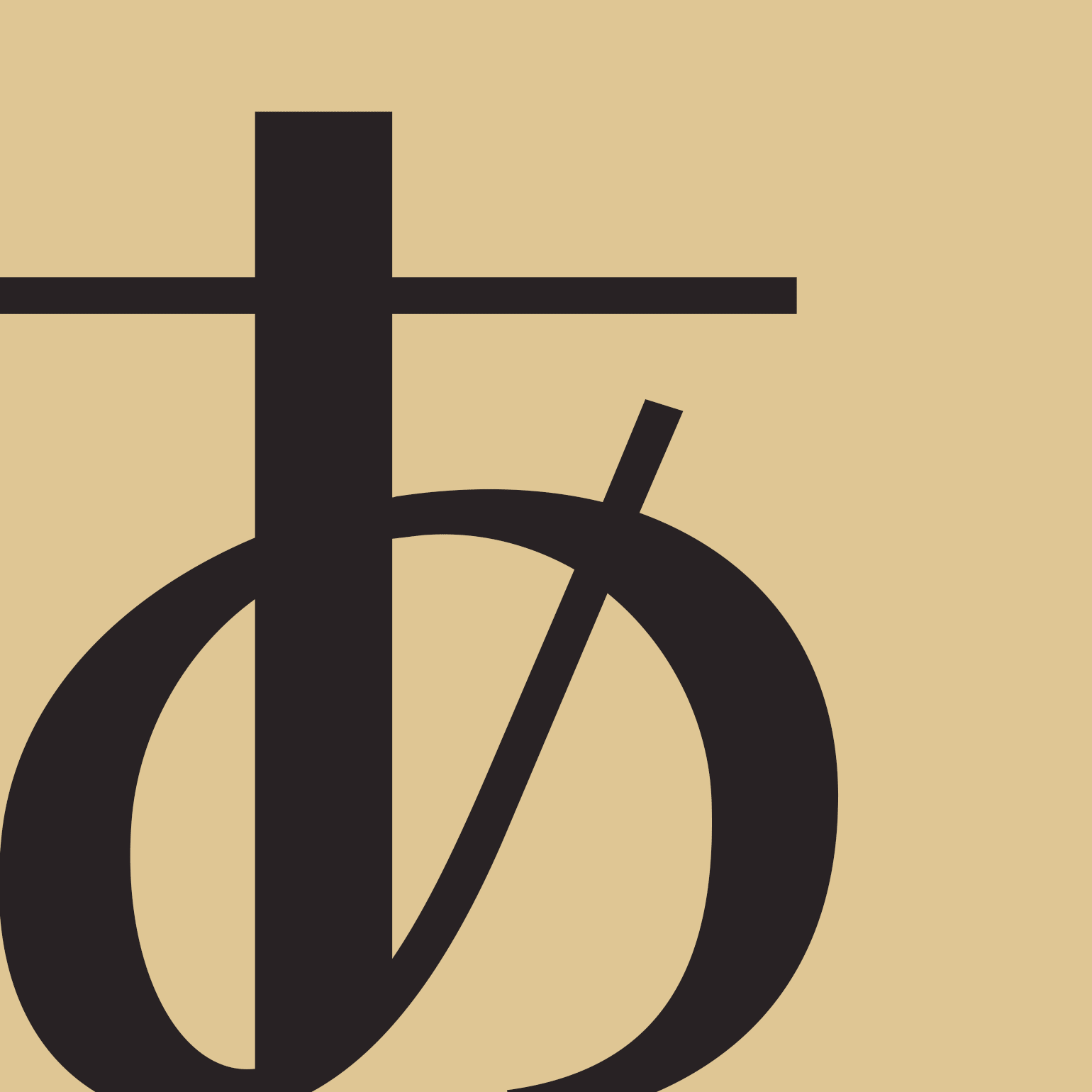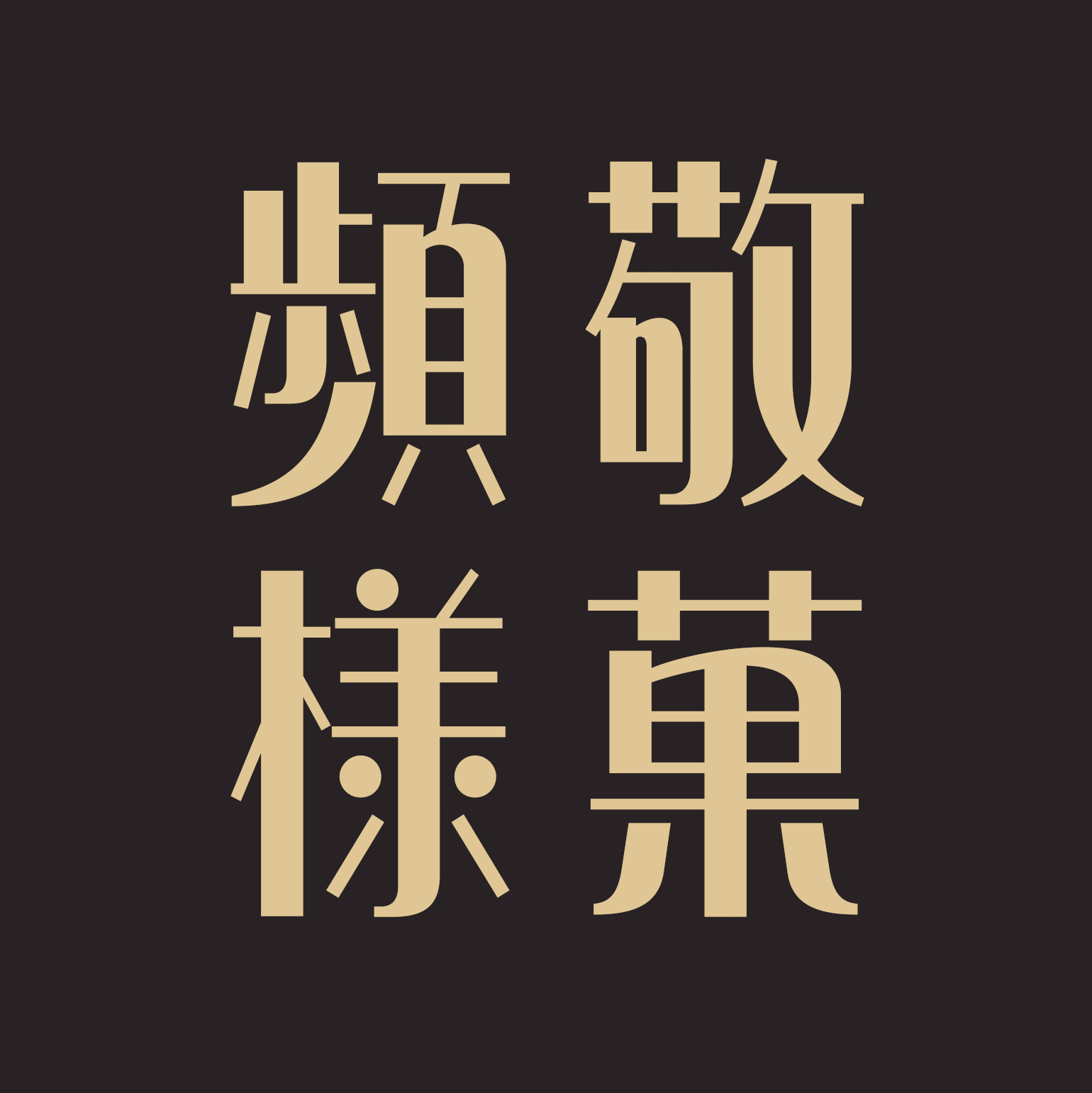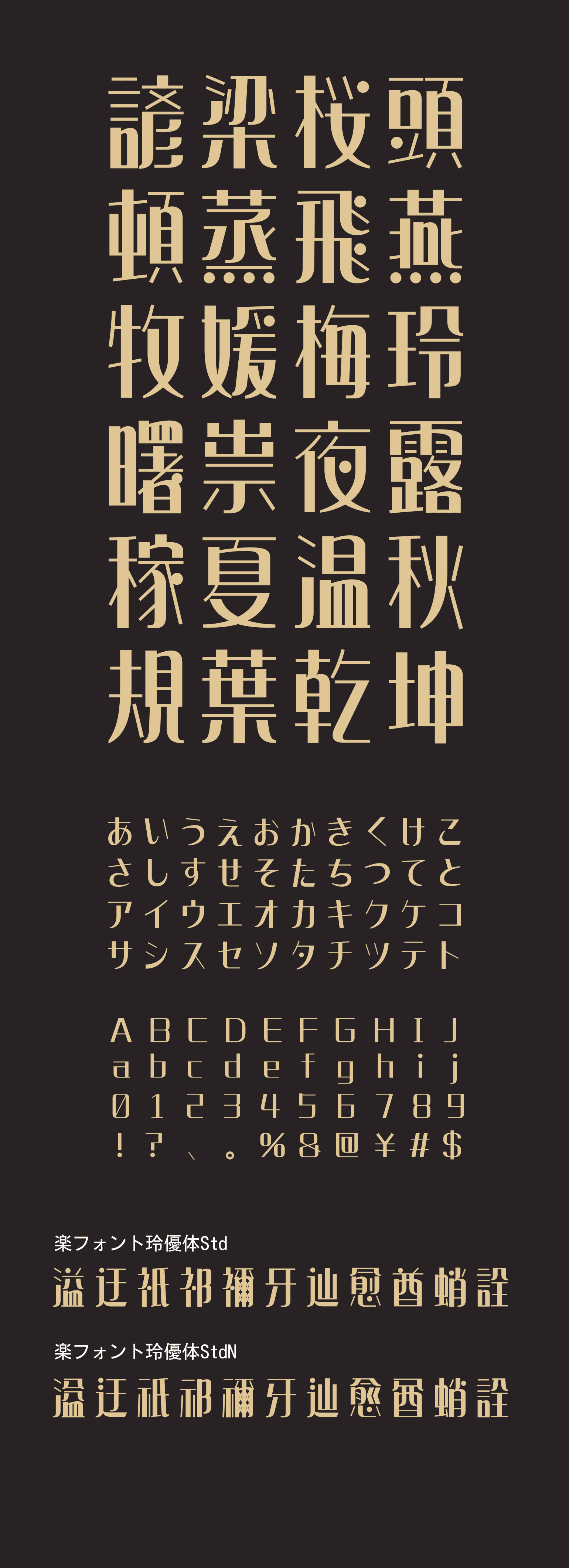
玲優体( れいゆうたい)
面相筆で描いたような筆使いが特徴で、レトロな親しみやすさを感じさせながらも、細長くスマートな字面の、洗練されたデザイン書体です。 画線は筆の運びと連動した抑揚を持ち、ハライにはアーク化を採用することによって、文字の中に生き生きとした表情を生み出します。 点は円形にすることにより、文字組の中に心地の良いアクセントを生みだしました。 反面、線のエッジは直角のラインでカッティングし、柔らかな雰囲気だけにとどめない二極性を。 優しい丸みと、鋭利な美しさが、さまざまな表現に可能性を与えます。